ひらがなの「ふ」ですが 、ふ←のように線が繋がっているバージョンの書き方を教えて下さい。正しい文字ではないのは承知の上です。よろしくお願いします。
お答えします(^^)
小学校で習う書写的な「ふ」はこんな感じですね。
ご質問にある「繋がっているバージョン」書いてみました。
「繋がっている」というのは、少し専門的な話をすると「行書的な要素がある」ということになります。
「正しい文字ではないのは承知の上です」とありますが、実は、繋がっていても間違いではありません。
文章の中で漢字を行書で書く場合、ひらがなもそれに調和させるため、繋げて書くことがあります。
平安時代の仮名文字「ふ」は、こんな風に書かれていました。
ちなみに、「ふ」の字源(もとになった漢字)は「不」です。
ワンポイント
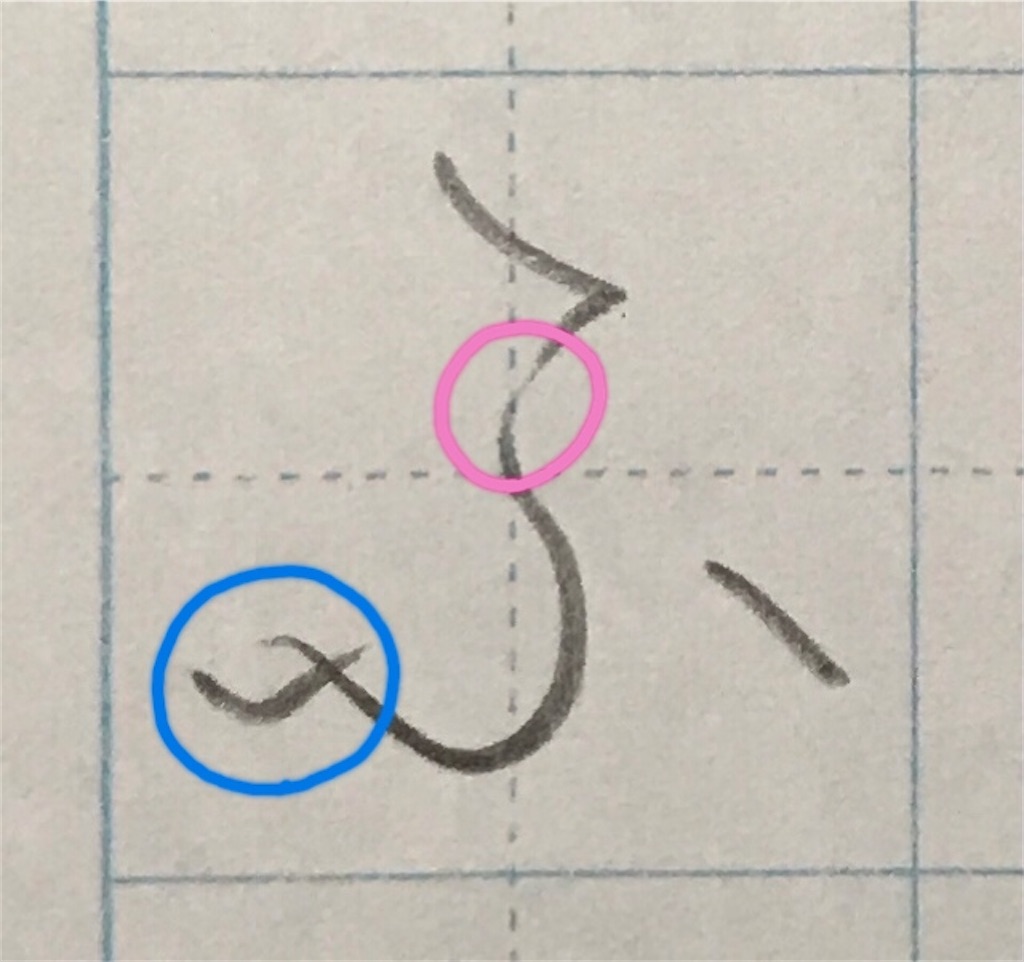
基本的な字形は写真1枚目と変わりません。
ピンク○→1画目と2画目の間で少し力を抜いて滑らかにすると良いです。
青○→ここは繋げるのが難しければ、1枚目のように離して書いてOKです。